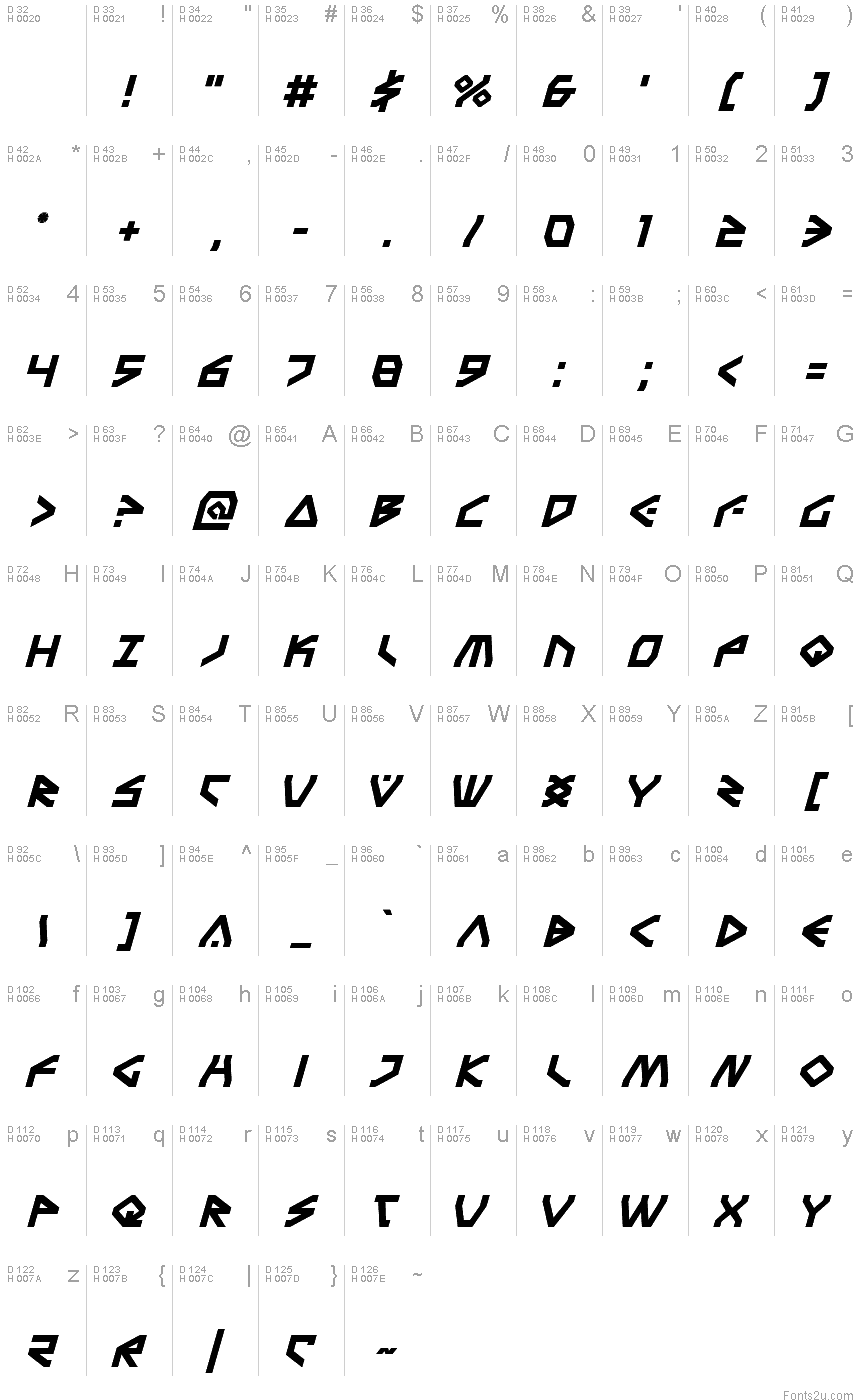
Terra Firma Italic
Terra Firma Italic von Iconian Fonts ist eine kantige Techno-Display-Schrift mit einer scharfen, vorwärtsdrängenden Ausstrahlung. Die Großbuchstaben wirken wie aus harten Facetten geschnitten; mit ihren spitzen Verbindungen, tiefen Diagonalen und offenen, dreieckigen Zwischenräumen verleihen sie dem Schriftbild einen schlanken, technoiden Rhythmus – weit weg von glattem Science-Fiction-Kitsch.
Sie passt perfekt überall dort, wo Sie einen Sci-Fi-Touch benötigen, ohne dabei komplett robotisch zu wirken: für Game-Logos, E-Sports-Branding, Plakatüberschriften, Albumcover und animierte Titelkarten. Als kostenlose Schrift überzeugt sie besonders bei kurzen Headlines, Monogrammen und Cover-Texten, wo die gezackten Großbuchstaben sofort ins Auge stechen.